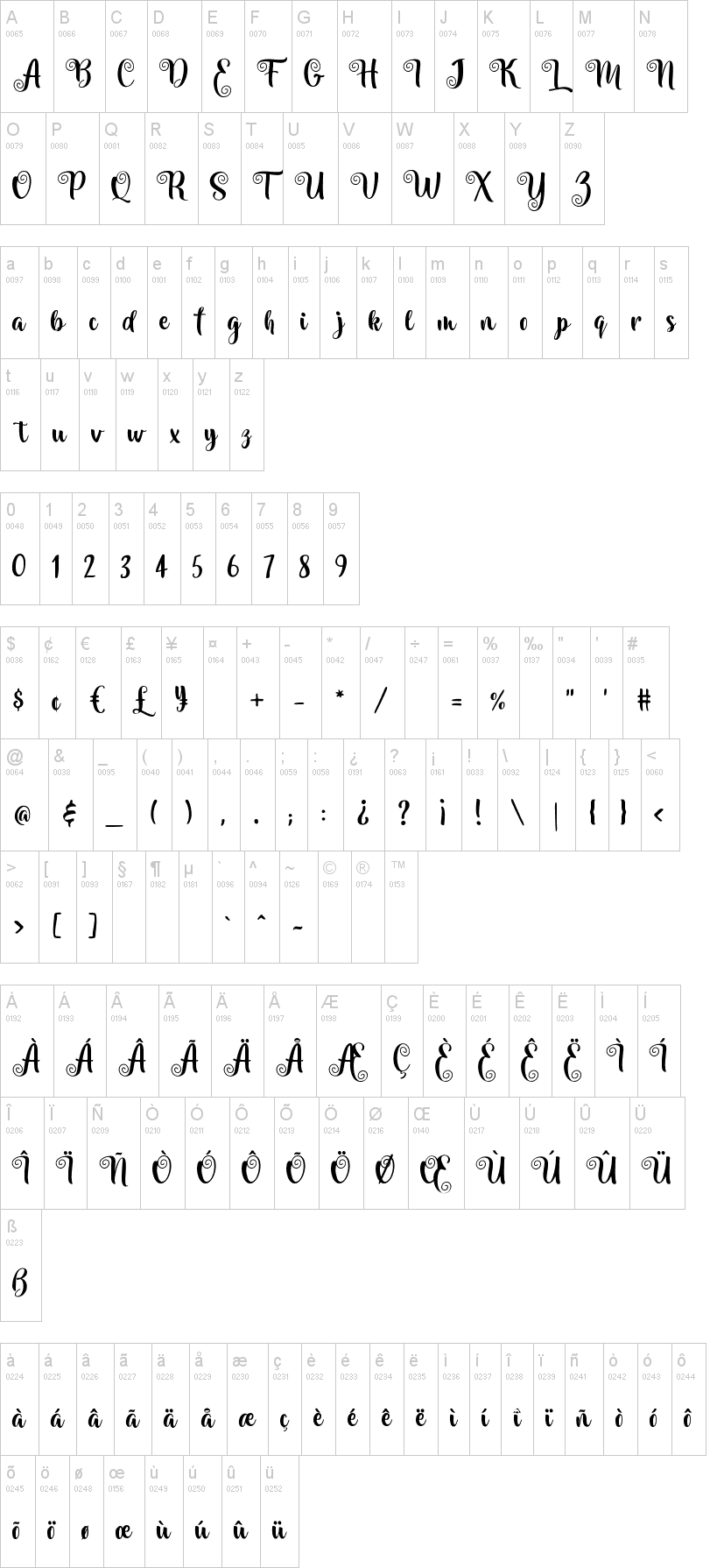
Amilya 字体是一款简洁时尚的手写体字体,由专业的设计师设计,拥有精美的笔画,给人一种清新自然的感觉。它的字体风格柔和,更适合用在品牌标识、海报、海报等设计中。它的字体细节精致,给人以精致的感受,更能凸显出设计的精细度。内容介绍
Amilya是一款非常不错的手写艺术字体,具有很好的视觉感,适合于文化类的宣传设计、商业类品牌的广告和产品包装设计以及个性化文字排版等较多场景。